دانلود Seasonal Collection Font Bundle مجموعه فونتهای انگلیسی فصلی با طرح های متنوع
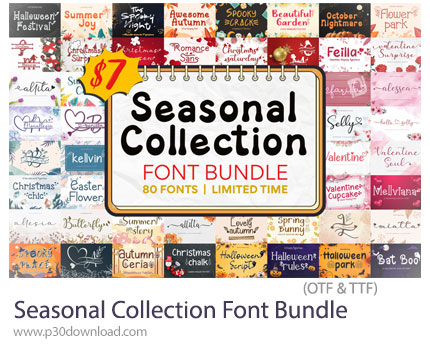
در این بخش شاهد 80 فونت انگلیسی فصلی با طرح های متنوع می باشید که با فرمت های OTF و TTF بر روی سایت برای دانلود قرار گرفته است. اگر به دنبال مجموعهای از فونتها هستید که در هر فصل و مناسب با هر مناسبت بتوانید خلاقیت خود را به نمایش بگذارید، این مجموعه فونت فصلی برای شماست. این پکیج بینظیر به طوری طراحی شده که به راحتی میتوانید از آن برای انواع پروژهها و مناسبتها استفاده کنید. چه در حال طراحی دعوتنامه عروسی باشید، چه گرافیکهای جذاب برای شبکههای اجتماعی یا حتی محصولات دیجیتال، این مجموعه فونتها هر آنچه برای ایجاد طرحهای بینظیر نیاز دارید را در اختیار شما قرار میدهد. شما میتوانید به راحتی از این مجموعه برای پروژههای مختلف خود استفاده کنید و طراحیهای خود را به سطح بالاتری ببرید. با این مجموعه فونت فصلی، شما میتوانید به راحتی طرحهای خود را برای هر مناسبت و فصل جذابتر و متناسبتر کنید.